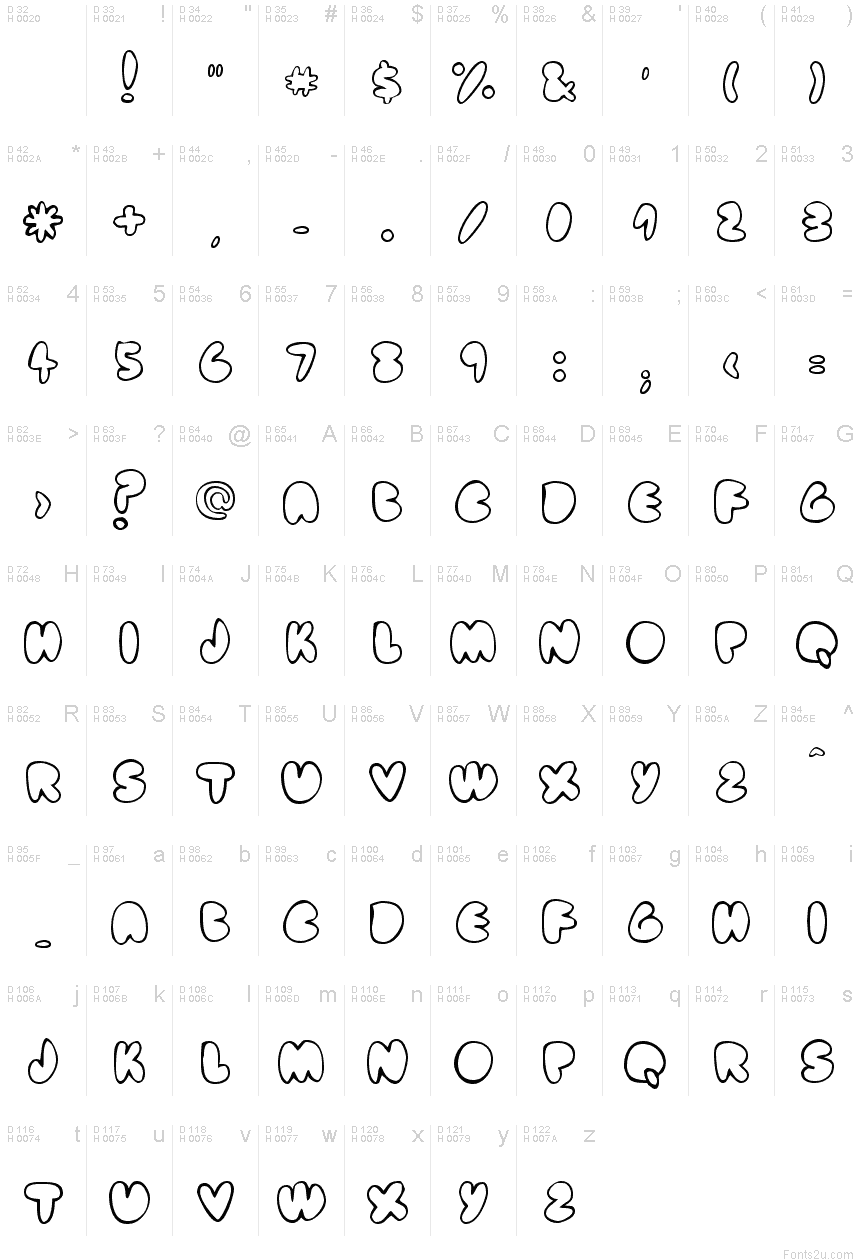
Fat Ass Outline, darmowy font komiksowy typu outline, stawia na efekt nadmuchanych liter typu „bubble” z zabawnym, odręcznym charakterem. Znaki wyglądają na miękkie, puszyste i lekko nierówne, a grube kontury i masywne kształty nadają całości wyrazisty, kreskówkowy styl.
Świetnie sprawdzi się na plakatach, grafikach z imprez dla dzieci, opakowaniach przekąsek, komiksowych nagłówkach, planszach tytułowych i wielkich monogramach – wszędzie tam, gdzie darmowy font z tak dużą dawką powietrza i wibracji będzie strzałem w dziesiątkę. Ponieważ wielkie litery są tak wydęte i proste, font najlepiej prezentuje się w krótkich hasłach i tytułach, pozwalając tym pulchnym sylwetkom grać pierwsze skrzypce.